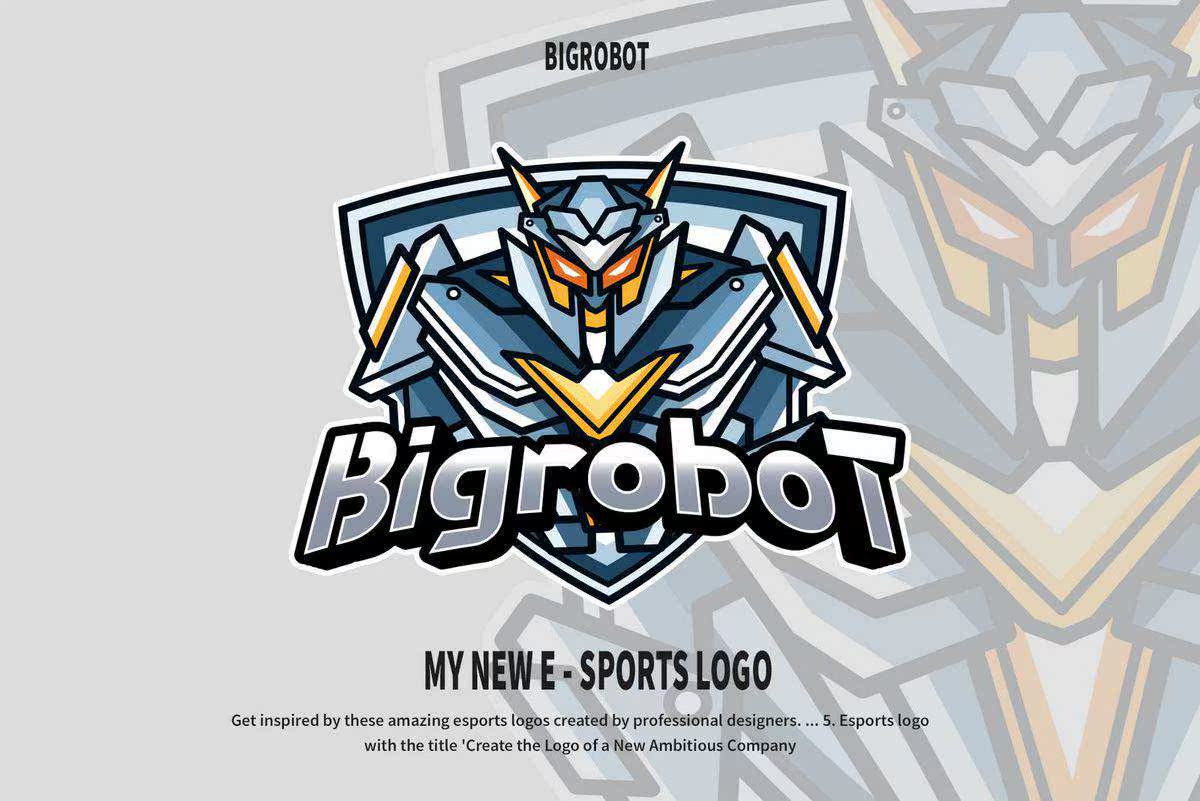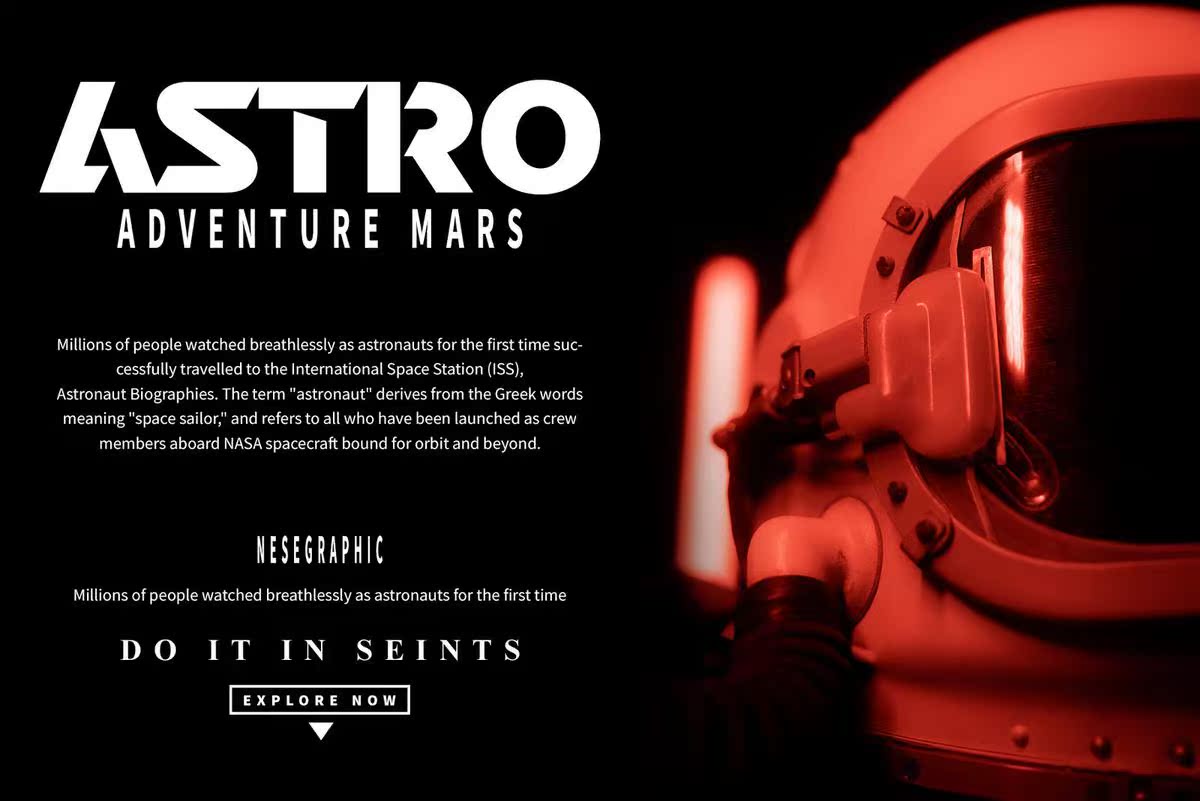
简介GourNewRelease,RoboticyBorgModernDisplayFont。此类型集适用于品牌徽标、邀请函、问候卡或任何类型的项目。通过多语言功能和样式变化,此类型将进一步增强您工作的外观。简介GourNewRelease,RoboticyBorgModernDisplayFont。此类型集适用于品牌徽标、邀请函、,欢迎卡,或任何类型的项目。具有多种语言功能和样式变化,这种字体将进一步增强您工作的时尚感。